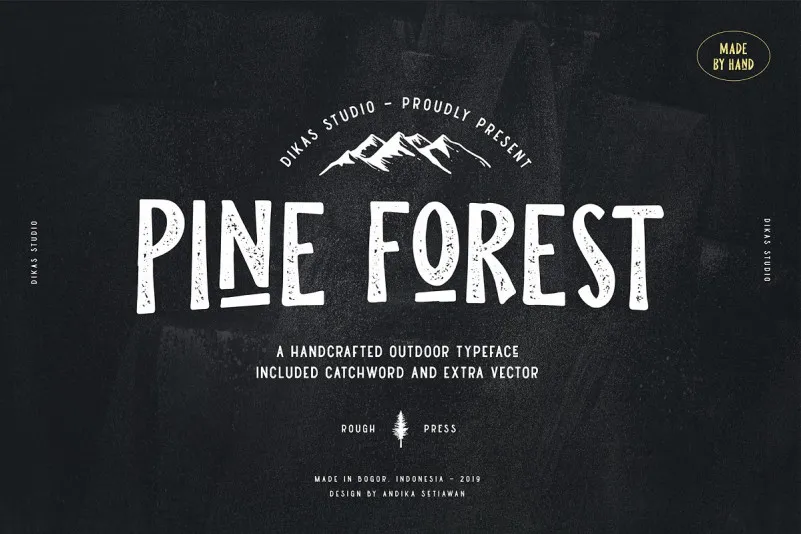
Pine Forest Font – Download Grátis
Pine Forest Font é uma elegante tipografia criada com mão dura para projetos vintage. Inspirada nas atividades ao ar livre, esta fonte leva um toque de sofisticação e nobreza, combinando um charme playfull que faz dela uma opção perfeita para estilos despojados e modernos. Perfeitamente adaptável a designs variados como logotipos, embalagens de produtos, cartões de convite, selos de identificação, materiais promocionais e outros tipos de artigos, Pine Forest traz dois diferentes estilos para escolher – uma versão suave e outra pressa. Essa fonte vem com um catchword extra e uma variedade de vetores úteis que podem auxiliar em sua criação de designs, tornando-a ainda mais versátil. Ideal tanto para designers profissionais quanto para quem está começando, a Pine Forest Font é perfeita para aqueles buscando uma tipografia única e inspiradora para seu próximo projeto.